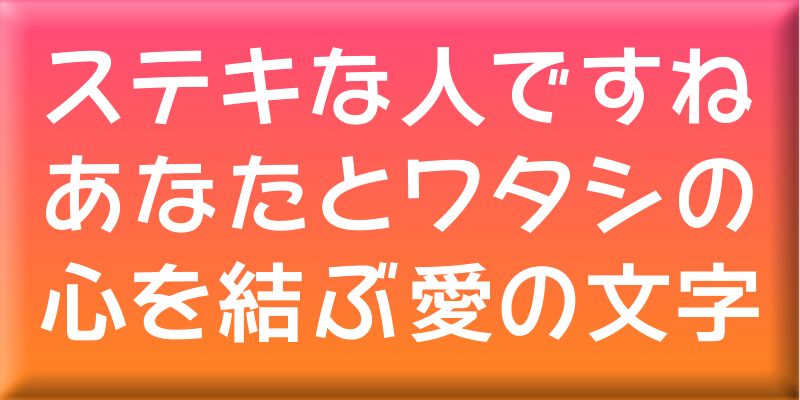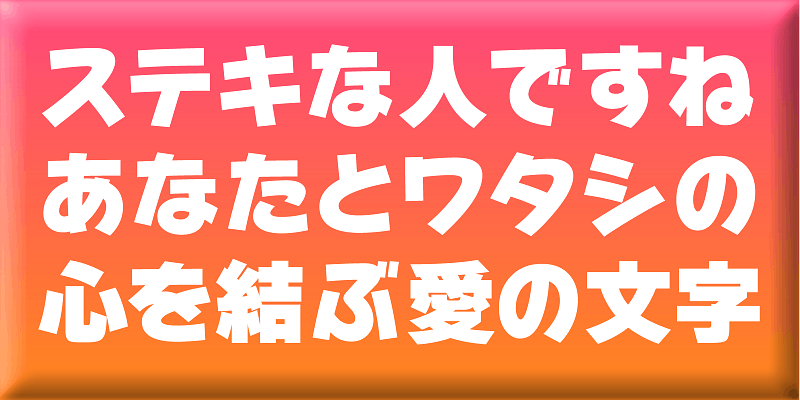
Diese einzigartige Schrift ist ein kaku-Gothic (quadratisches Sans-Serif) Design, das jedoch sehr hell und weich wirkt. Ihre Striche haben geradlinige und dennoch dynamische Kurven. Ihre Stabilität und Nützlichkeit bei der Textgestaltung sind weithin bekannt.